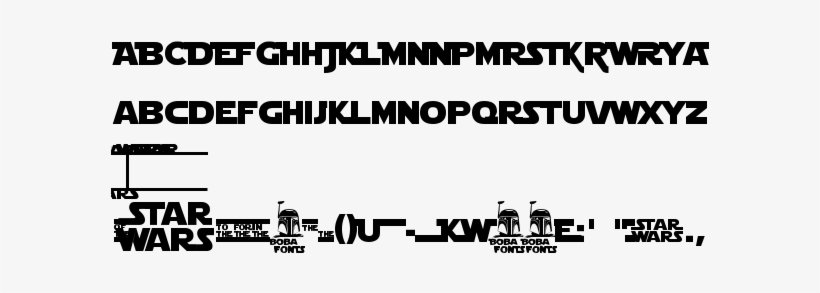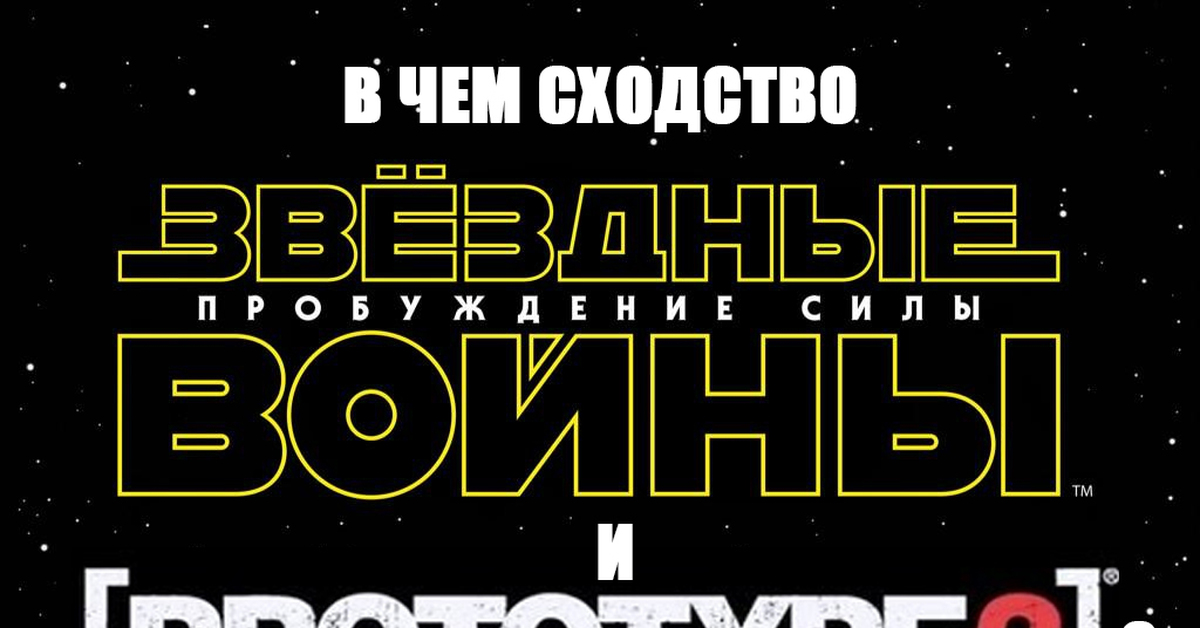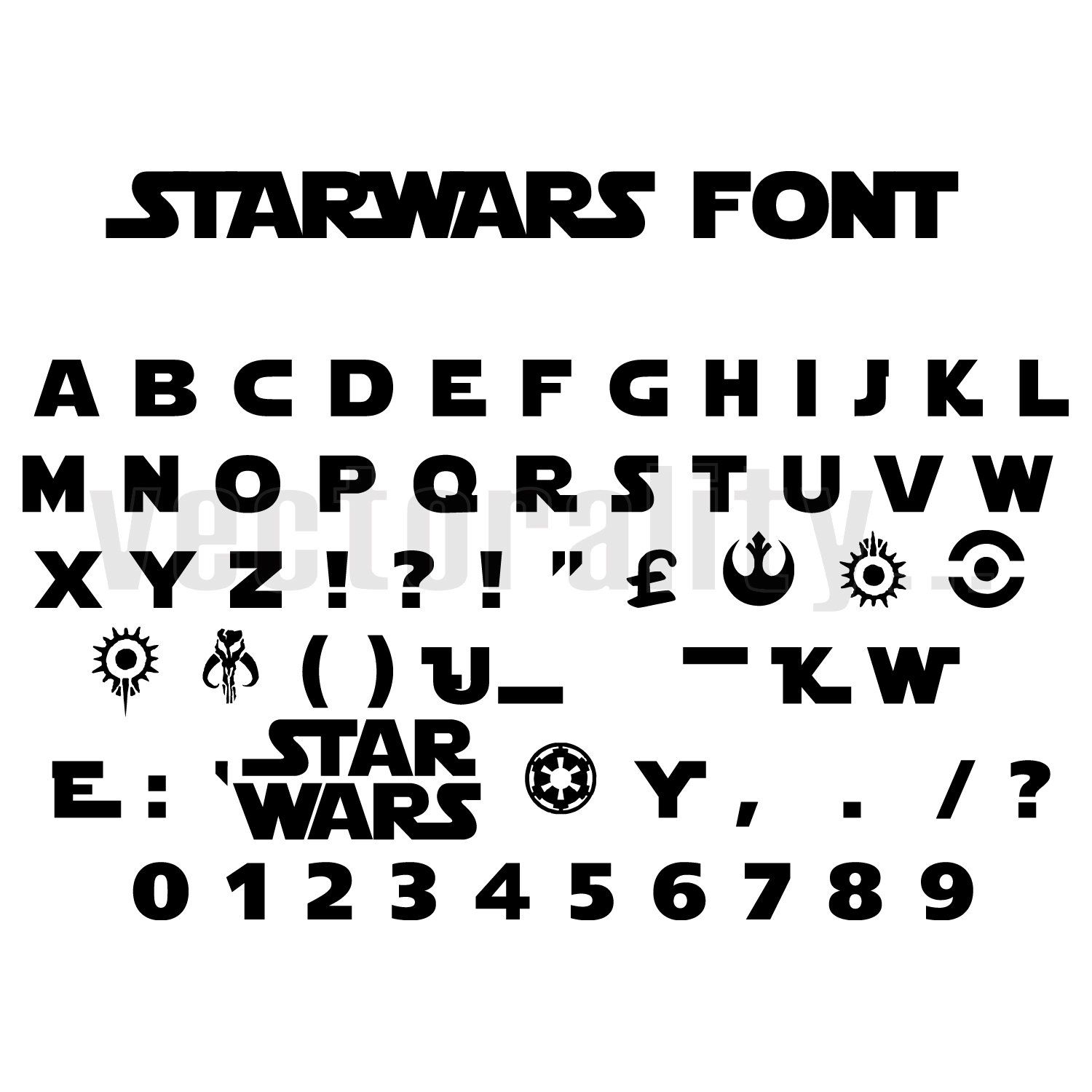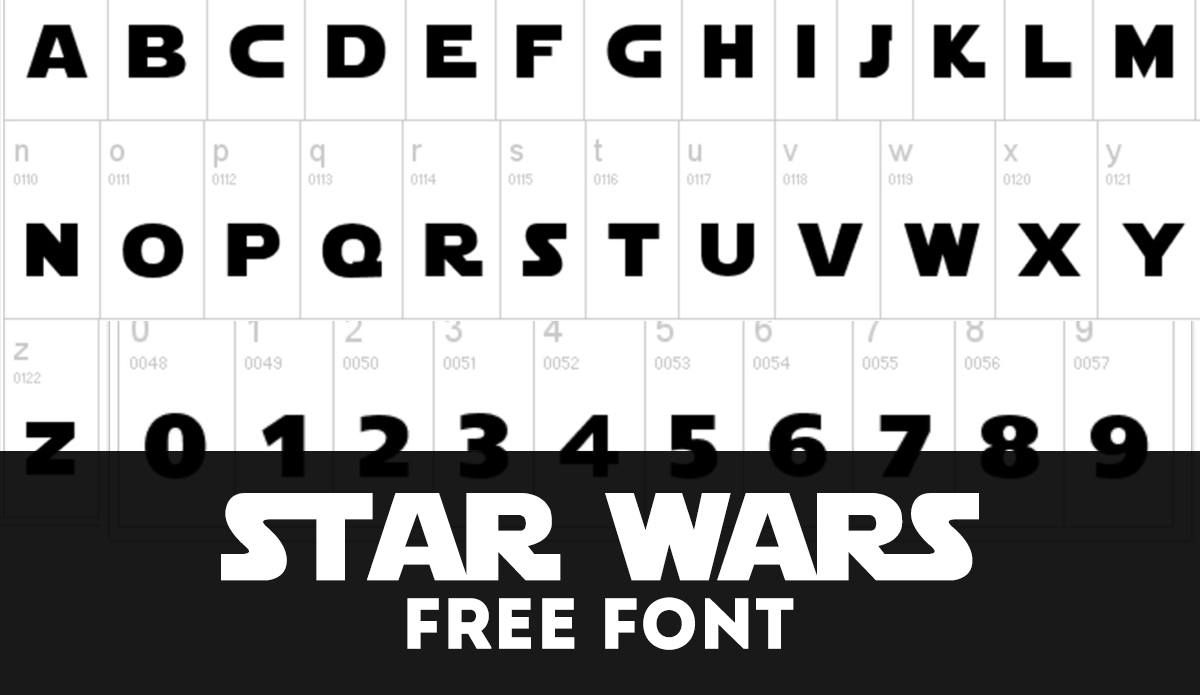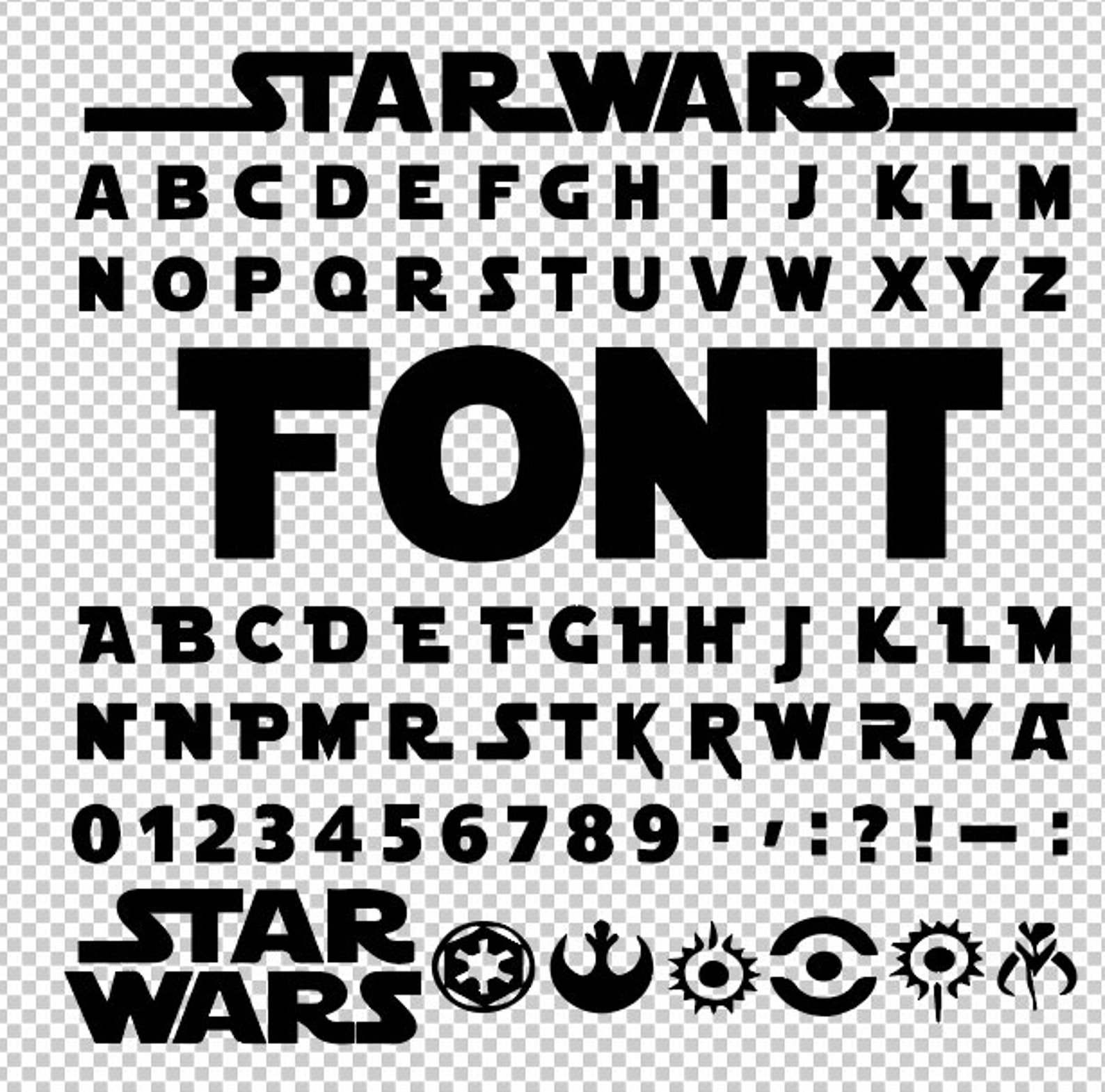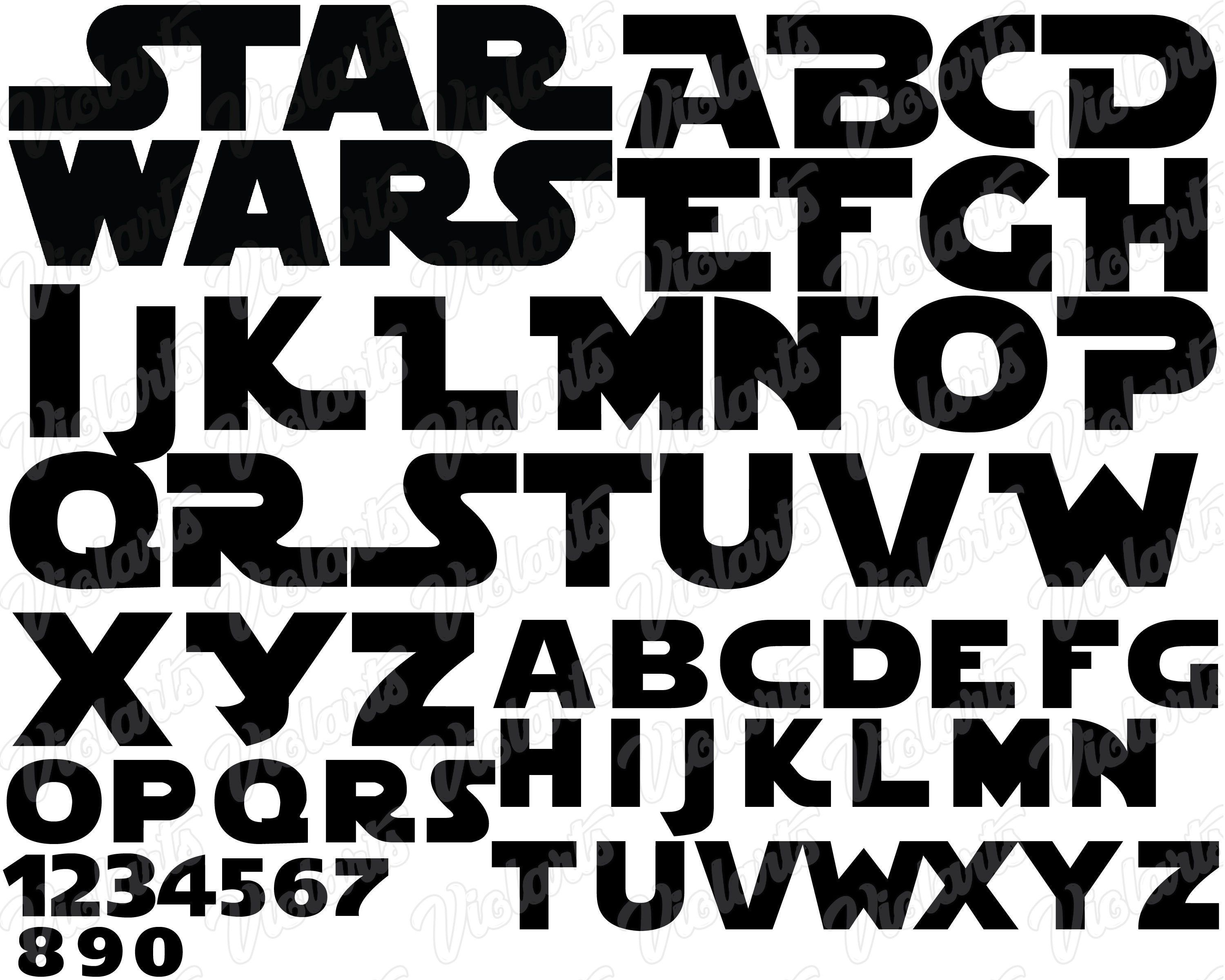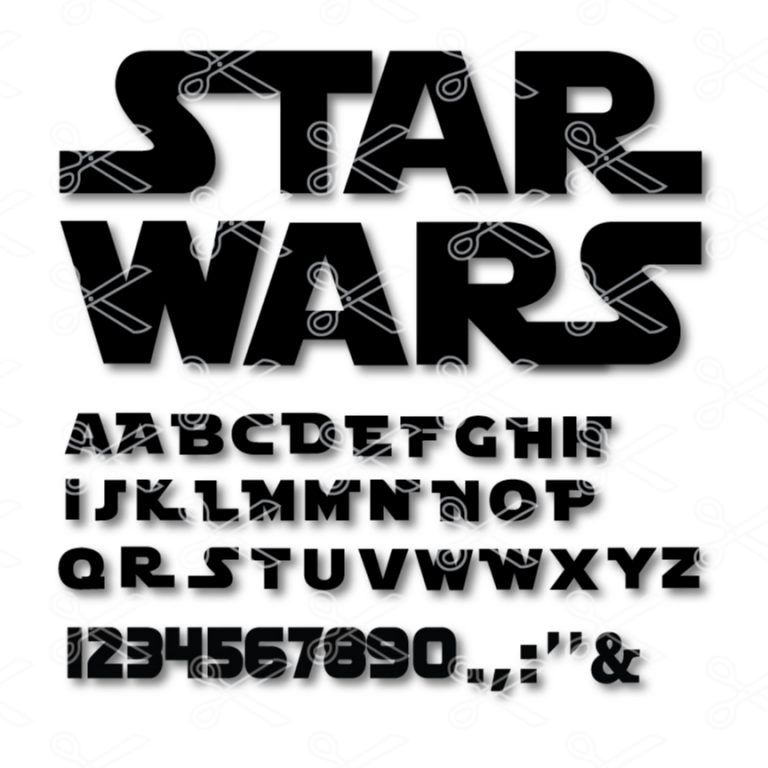
Лучшие научно-фантастические и техно шрифты для футуристического дизайна
В этом посте мы представляем вам одни из лучших техно- и научно-фантастических шрифтов, которые вы можете использовать в своих футуристических проектах. Независимо от того, разрабатываете ли вы интерфейс игры или нуждаетесь в шрифте, дополняющем научно-фантастическую тему ваших эскизов видео на YouTube, блогов, публикаций в социальных сетях или постеров, эти шрифты помогут вам создать атмосферу и стиль космической эры.
Ниже вы найдете сочетание различных стилей шрифтов, включая минимальные современные шрифты (Anurati), моноширинные шрифты (Space Mono), геометрические шрифты без засечек (Orbitron) и шрифты с квадратными буквами (Neuropol). Большинство этих шрифтов разработаны как гарнитуры для заголовков и заголовков, в то время как некоторые из них, такие как Exo, имеют разный вес и достаточно универсальны, чтобы их можно было использовать и в основном тексте. Обладая научным и технологическим чутьем, эти шрифты идеально подходят для тех случаев, когда вы хотите, чтобы ваши дизайны создавали высокотехнологичное футуристическое впечатление.
Бесплатные шрифты в стиле техно и футуристической научной фантастики
1. Anurati – бесплатный футуристический шрифт
Anurati – бесплатный футуристический шрифт от шрифтового дизайнера Эммерана Ричарда. Шрифт только в верхнем регистре, он имеет минимальные буквы, созданные с отрицательным пространством. Современный шрифт, который можно использовать в дизайне плакатов, заголовков и обложек книг. Доступный для бесплатной загрузки в формате OTF на Behance, Anurati бесплатен для личных и коммерческих проектов.
2. Ailerons – ретро футуристический шрифт
Разработанный как часть экспериментального проекта Адилсона Гонсалеса, Ailerons черпает вдохновение в моделях самолетов 1940-х годов. Элероны отличаются уникальным сочетанием острых и мягких закругленных углов. Его чистые высокие буквы добавят стильный ретро-футуристический вид вашим заголовкам и заголовкам. Шрифт поставляется с лицензией на личное использование. Скачать бесплатно в формате OTF.
3. Astro – Космический шрифт
Astro – это модульный шрифт с эстетикой трафаретных шрифтов. Вертикальный сжатый шрифт Astro вдохновлен астрономическим миром и идеально подходит для дизайна космической тематики. Созданный испанским дизайнером Глорией Флорес Ллеонарт, его можно бесплатно скачать в формате TTF.
4. Alexana Neue – Минимальный шрифт
Alexana Neue – это минималистичный абстрактный шрифт, вдохновленный космосом.
Шрифт, написанный прописными буквами, отлично подойдет для создания футуристических дизайнов космической эры, плакатов и проектов брендинга. Шрифт, выпущенный Марком Мора, является бесплатным для некоммерческого использования и доступен для загрузки в формате TTF.
5. Space Mono – футуристический шрифт Google
Space Mono от Colophon Foundry – это семейство моноширинных дисплеев (фиксированной ширины) с ретро-футуристической атмосферой. В его буквенных формах присутствуют геометрические и гротескные мотивы, схожие с гарнитурами заголовков 1960-х годов, такими как Microgramma и Eurostile, которые широко использовались в популярных научно-фантастических фильмах (2001: Космическая одиссея, Звездный путь) и на телевидении.
Space Mono – это шрифт с открытым исходным кодом, доступный в Google Fonts, он имеет два веса: обычный и полужирный с соответствующим курсивом. Он также поддерживает расширенный набор латинских глифов. Формат шрифта: TTF.
6. Orbitron – Научно-фантастический шрифт Google
Orbitron – это бесплатный геометрический шрифт без засечек, разработанный как шрифт для использования в футуристических научно-фантастических проектах. Он доступен в четырех вариантах толщины – Light, Medium, Bold и Black и включает стилистические варианты, маленькие заглавные буквы и альтернативные глифы.
Orbitron – это шрифт с открытым исходным кодом от The League of Moveable Type. Он также доступен в Google Web Fonts. Загружаемый файл включает шрифт в форматах TTF, OTF, EOT, WOFF и SVG.
7. Neuropol – бесплатный шрифт Techno
Neuropol – это научно-фантастический шрифт, созданный Typodermic Fonts. Его квадратный дизайн с закругленными углами основан на популярных техно-шрифтах Microgramma и Chimes. Усеченные горизонтальные штрихи в некоторых его символах, таких как строчные e, a, прописные s и числа 2 и 5, имитируют следы лазерного или векторного луча.
8. Exan-3 – Шрифт
Exan-3 – моноширинный футуристический шрифт от графического дизайнера Джона Карлоса. Он состоит из прописных букв и цифр. Идеально подходит для плакатов, визиток и заголовков. Шрифт поставляется с бесплатной лицензией на коммерческое использование. Доступно для скачивания в формате TTF.
Можно ли использовать шрифт Star War бесплатно?
Где можно использовать этот шрифт?
Этот шрифт на основе логотипа является идеальным шрифтом для целей дизайна логотипа. Кроме того, вы также можете использовать этот шрифт во многих своих дизайнерских проектах, таких как баннеры, брошюры, названия фильмов, СМИ, дизайн веб-сайтов, презентации, реклама и сообщения в социальных сетях.